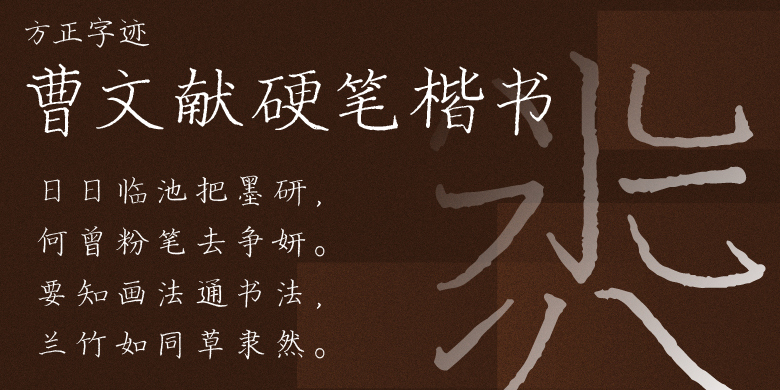
方正字迹-曹文献硬笔楷书
方正字迹-曹文献硬笔楷书,这款字体结构工整、笔画清晰,兼顾美观与易读性,适用于标题、正文、海报、包装、LOGO 等多种场景。字形优雅稳定,风格百搭耐看,适配日常排版与创意设计,让文字呈现更舒适、更具质感。方正字迹-曹文献硬笔楷书一笔一画,皆是细节,以均衡的比例、流畅的线条打造舒适视觉体验,字形端正大气,风格简约现代。无论是商业设计、品牌宣传还是日常排版,都能轻松驾驭,让文字更有格调与力量。方正字迹-曹文献硬笔楷书字体下载。
曹文献
字体分类:
常规书写·硬笔
随着时代进步和发展,钢笔的使用渐渐地淡出历史舞台,当下日常书写工具变成了中性笔为主,但是市面的楷书硬笔书法教材主流还是用钢笔书写的,其特点书写速度较慢,节奏感不强,需要花费更多的时间书写,实用性却大打折扣,给中小学作为参考字体,确实有些不符。因此,我苦心钻研硬笔书法多年,摸索出一套中性笔楷书的书写方法技巧,以实用性为主,其特点书写流畅,写的规范工整,能写出节奏变化和粗细变化,可以做到写好写快,字库中所有字均为普通中性笔书写,当用同样的笔书写出来的字,才更适合给中小学生作为日常书写的参考,其适用于硬笔规范字教材字体使用,以及国学文化、商业类品牌的广告语设计。